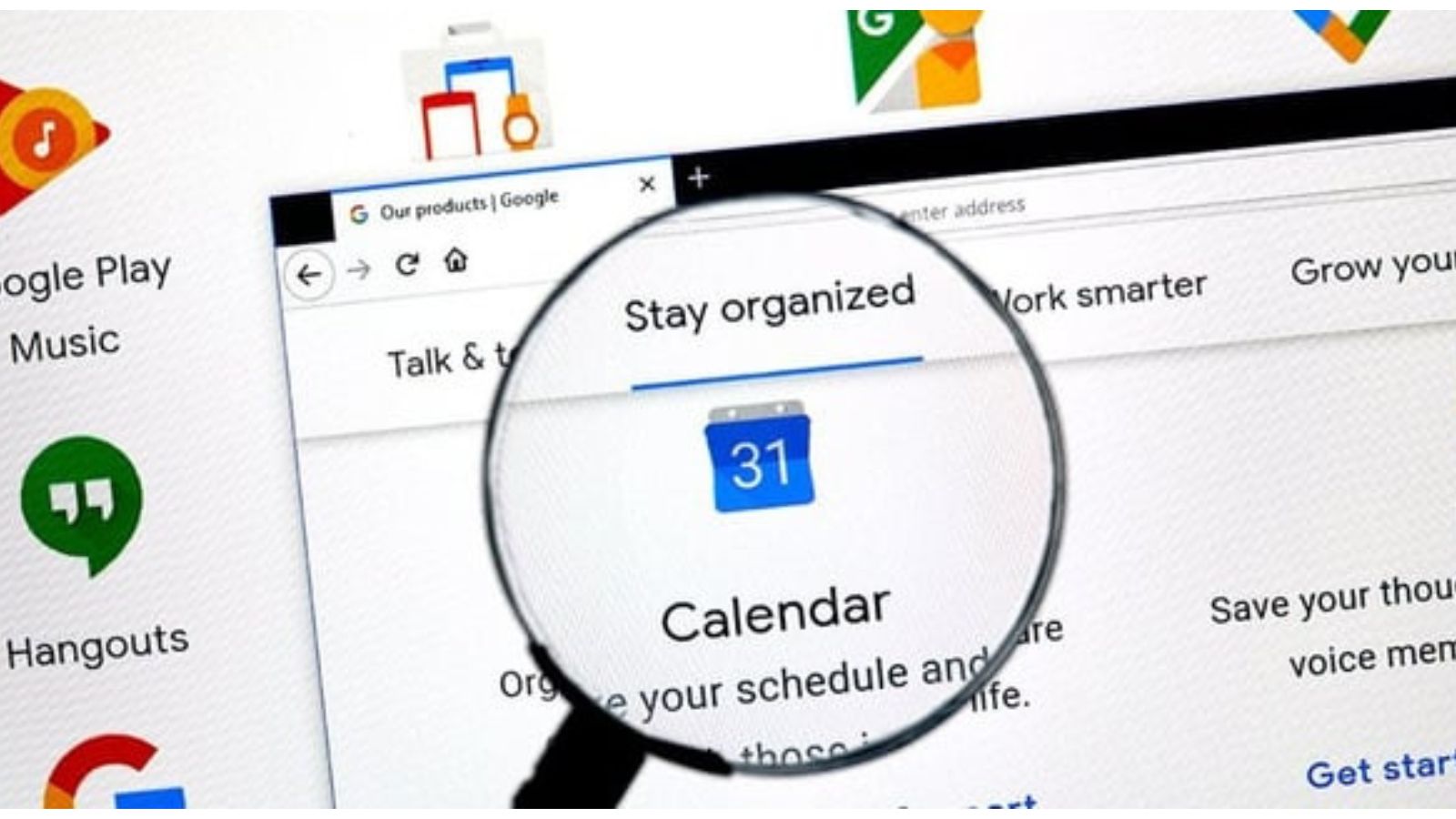
Google sta lavorando a un aggiornamento di GoogleCalendar che porterà con sé importanti novità. Tra le modifiche previste, vi è una nuova impostazione che permetterà di controllare meglio la condivisione delle informazioni con altre applicazioni di calendario. Al tempo stesso, l’app riceverà un aggiornamento estetico. È previsto infatti l’ inserimento di un nuovo font che renderà l’interfaccia più moderna e leggibile.
Un nuovo look per Google Calendar
Attualmente, quando un utente concede a un’applicazione il permesso di accedere al calendario, quest’ultima può ottenere informazioni tramite l’API Calendar Provider di Android. Tale meccanismo consente di sincronizzare gli eventi tra diverse app. Però non offre un controllo dettagliato sulla condivisione dei dati. Google vuole cambiare questa situazione introducendo un’opzione che permetterà di impedire l’accesso ai propri eventi da parte di altre applicazioni.
La nuova funzione potrebbe rivelarsi particolarmente utile per chi utilizza più calendari sullo stesso dispositivo e magari desidera mantenere separati gli appuntamenti personali da quelli gestiti da app di terze parti. Non è ancora chiaro quando questa novità sarà disponibile per tutti, ma il suo sviluppo è stato individuato nell’ultima versione dell’app. Il che suggerisce che potrebbe essere rilasciata nei prossimi giorni.
Oltre alla funzione dedicata alla privacy, Google sta lavorando anche a un piccolo ma interessante cambiamento estetico. L’app infatti adotterà il font Google Sans Flex, introdotto dall’azienda nel 2023, ma finora poco utilizzato nelle sue applicazioni.
Rispetto al carattere attuale, il nuovo font appare più spesso e arrotondato, migliorando la leggibilità dell’interfaccia. Questa scelta rientra in una più ampia strategia di aggiornamento grafico che Google sta applicando ai suoi servizi per garantire maggiore uniformità e coerenza visiva. Insomma, con tutti questi cambiamenti, GoogleCalendar si prepara a diventare un’app ancora più sicura e gradevole da usare. Il suo scopo è quello di offrire un’esperienza ancora più personalizzabile e moderna che mai.